Binnenmajuskel
»Binnenmajuskel« ist ein typografischer Terminus für eine Majuskel (Großbuchstabe) eines altgriechischen oder römischen Alphabets inmitten von Minuskeln (Kleinbuchstaben), wie sie beispielsweise innerhalb eines Eigennamens von Personen, Firmen oder Produkten in gemischter Schreibweise (Groß-/Kleinschreibung) ohne Leerraumzeichen vorkommt, z.B. wie in MacLeod, McDonald’s ® oder iPhone ®; Großbuchstabe zwischen Kleinbuchstaben.
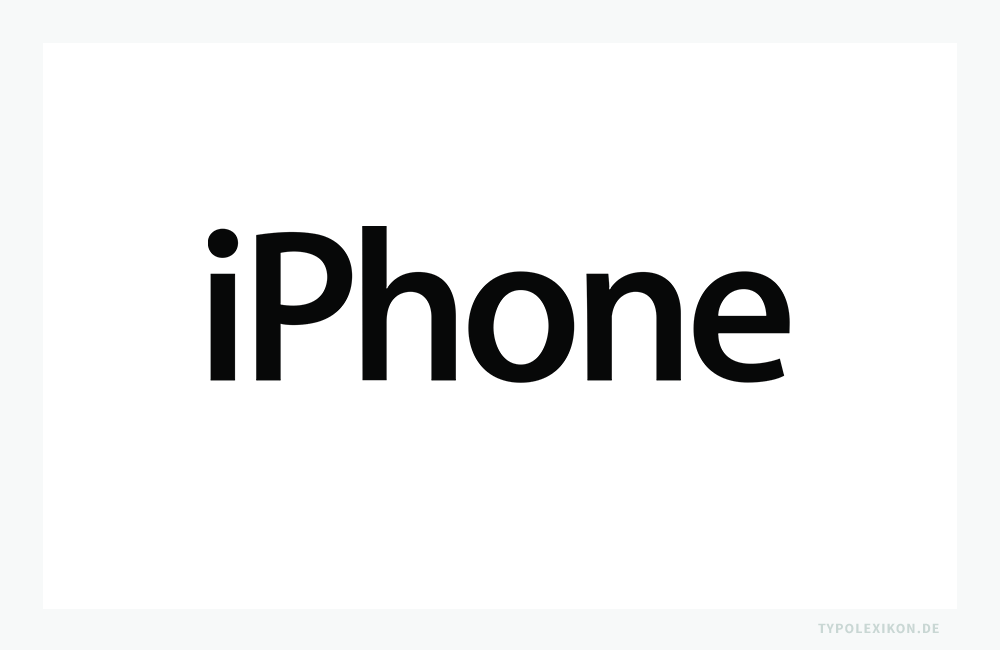
Ursprünglich stammt die Binnenmajuskel aus der zusammengezogenen Schreibweise von Vorsilbe und Familienname bzw. Clanname, wie der bereits oben erwähnte schottische Clanname »MacLeod«, wobei in diesem Fall die Vorsilbe »Mac« soviel wie »Sohn von« Leod bedeutet.
Heute werden auch Markennamen, bspw. die BahnCard ® der Deutsche Bahn AG, mit einer Binnenmajuskel geschrieben, um aus der Sicht des Vertriebs, Marketings und Corporate Designs mögliche Synergieeffekte zu erzielen.
Etymologisch rührt »Binnen« aus dem mhd./mnd. »binnen« von »bi innen« für »innerhalb« und »Majuskel« vom mlat. »maiuscula (litera)« zu lat. »maiusculus« für »etwas größer« zu lat. »maior, maius« für »größer«.